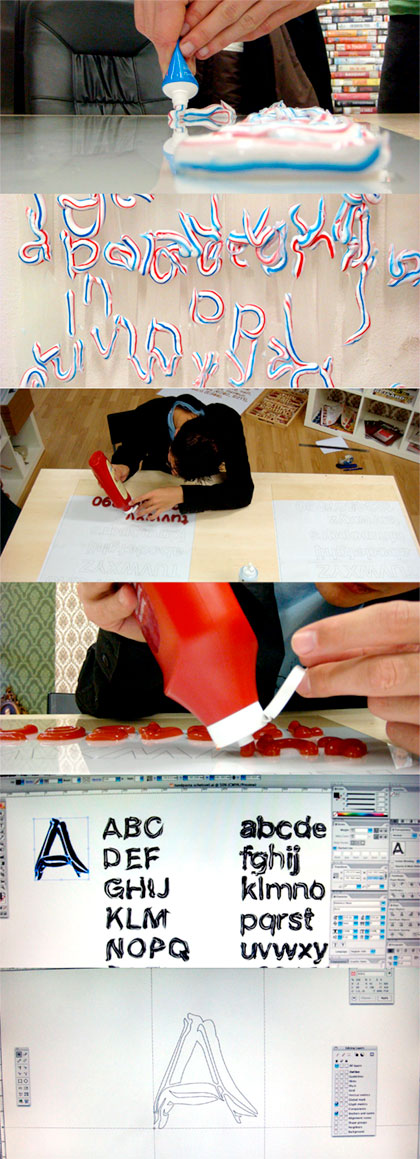
Quand on découvre dans ses fils RSS quelques images fugaces, au milieu de centaines qui défilent chaque jour, on dispose que de qq secondes pour prendre du recul et classer, associer, se remémorer, et finalement avoir une chance de décrypter. Ainsi par exemple sur le site de Fubiz , j’avais aperçu une série d’images avec des qualificatifs dithyrambiques, oui des photos re-montées, collages numériques qui perso me rappelaient les collages de David Hockney… ah merci M’me, pour le quart d’heure culturel.
Je t’en ficherai du culturel, quand ça vous arrange vous appelez ça référent culturel, et quand ça vous arrange autrement vous appelez cela des référents catégoriels, c’est à la demande et ça se débite comme du ketchup ou de la pate à dentifrice.
Tiens j’y arrive, voilà le tube que je cherchais, Kraftwerk, un morceau du groupe Autobahn —enfin j’ai compris l’intention des créateurs de freshfonts— … Kraftwerk donc, jadis co-fondateurs de la musique (techno ou) electro (dans les années 70) et du coup on comprend mieux la filiation de ce studio hollandais qui y fait référence en empruntant jusqu’au nom du célèbre groupe son patronyme. Typo Techno, Typo FontLab, Typo expérimentale… je vais pouvoir continuer de bosser heureux de pas mourir idiot. J’avais bien d’autres références en tête et notamment le Blur de Neville Brody mais ne suis pas sûr qu’il soit «parti» d’un matériau aussi brut pour redessiner son caractère.